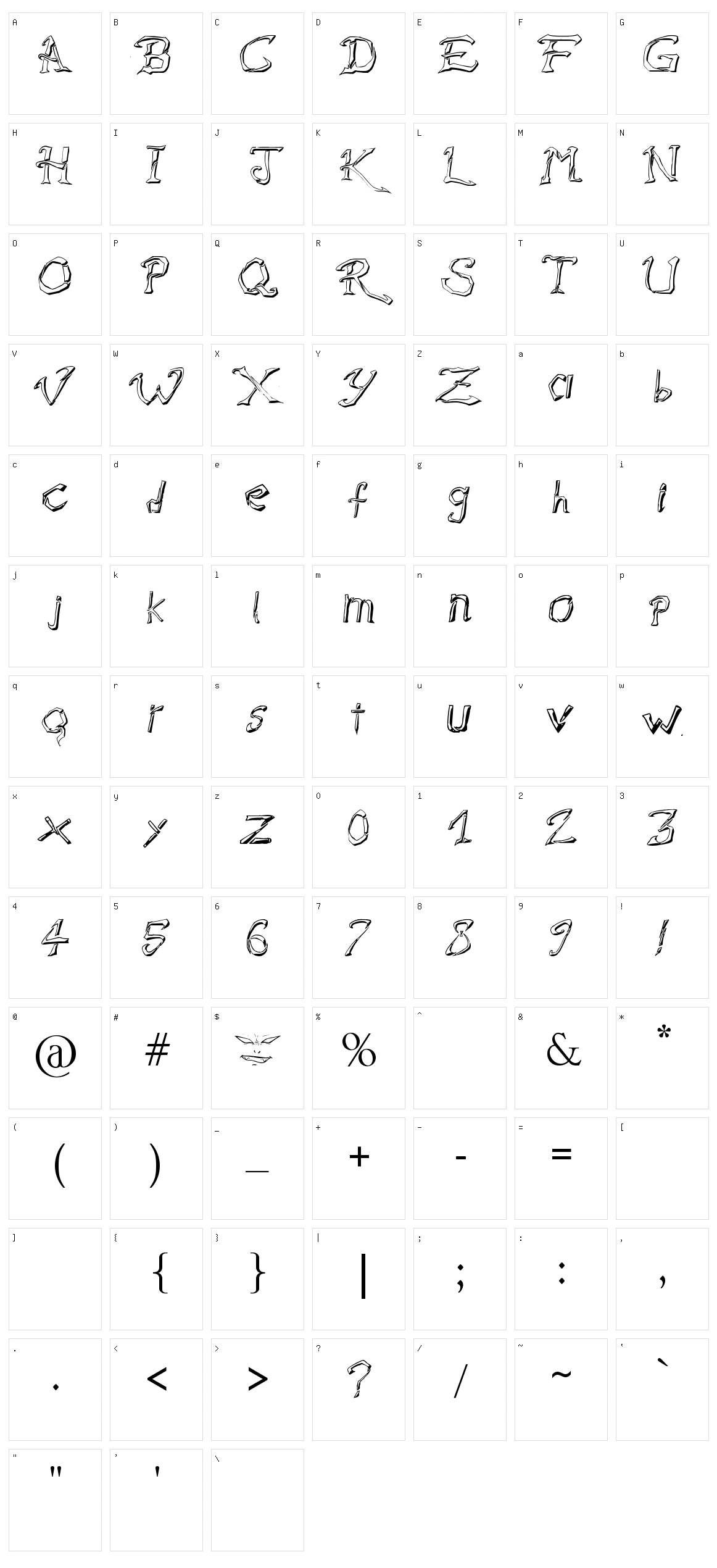
Vous venez d'aquérir à peu près légalement le font (police) "Raslani Destroyed Souls"
Il s'agit d'une écriture d'abord manuscrite puis scanée et assemblée pour en faire une police pour vos documents,
vos montages, ou autres choses dans le même goût.